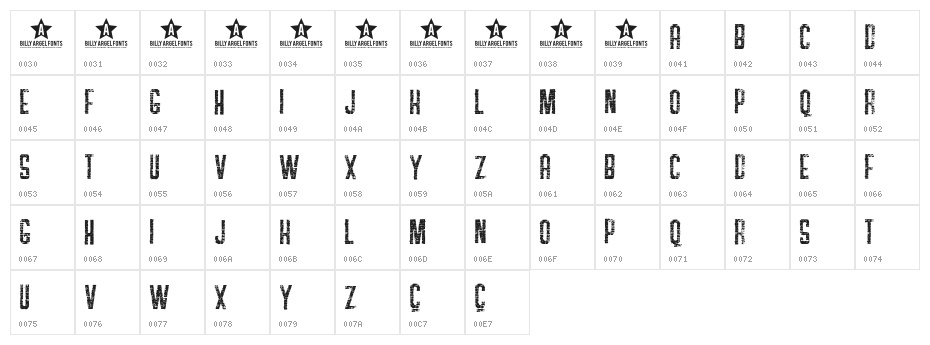
SOAPSTORE Font
| Progetti proposti | Ideal for vintage-themed posters, album covers, branding for rustic or industrial products, and any design requiring a bold, textured statement. |